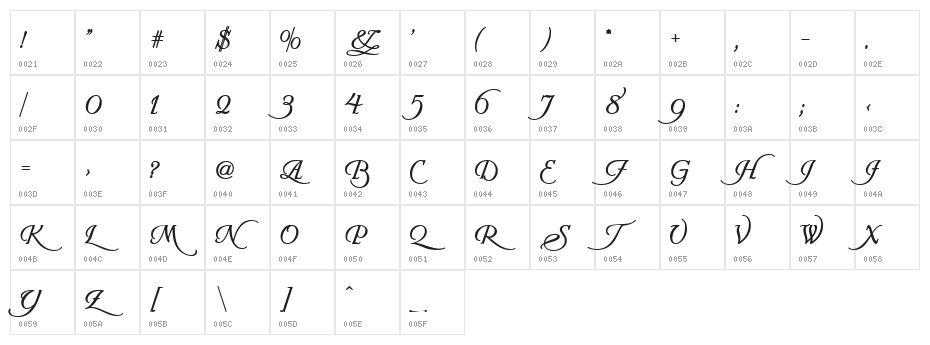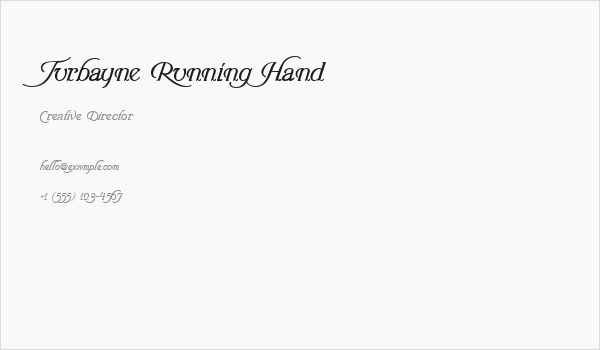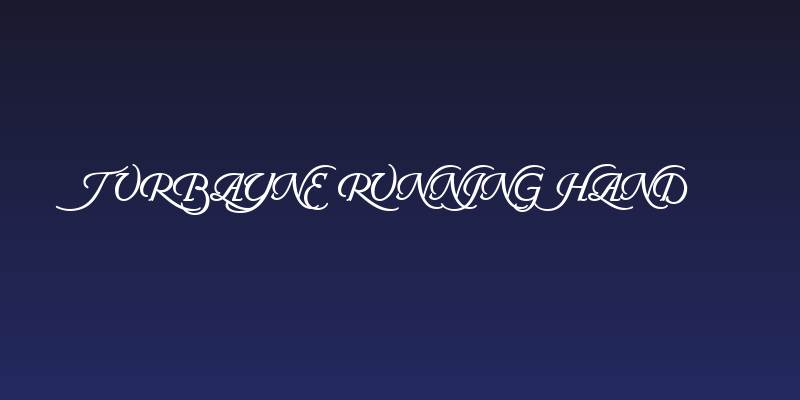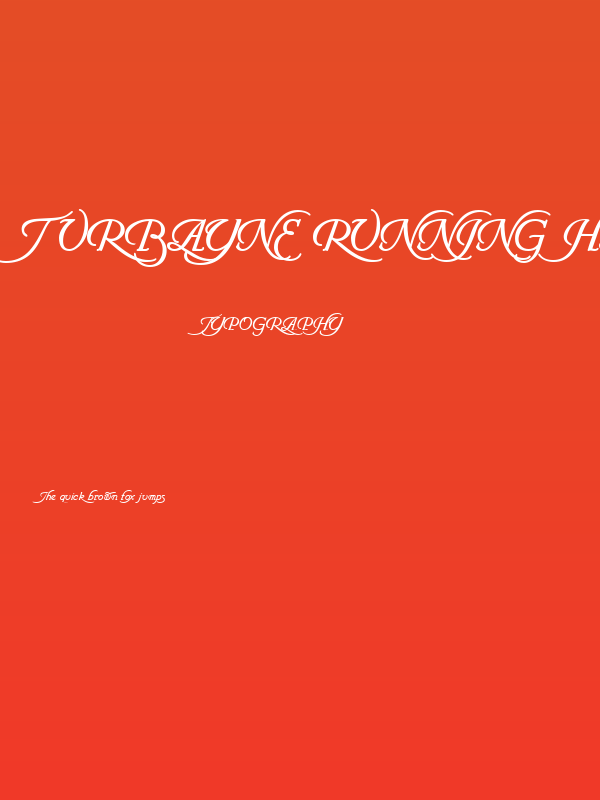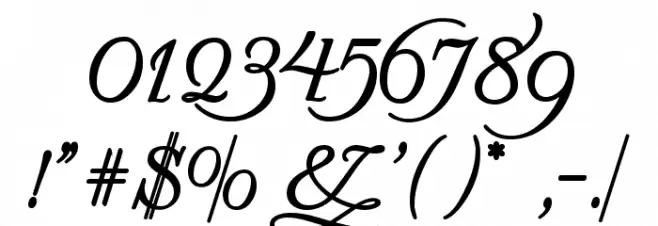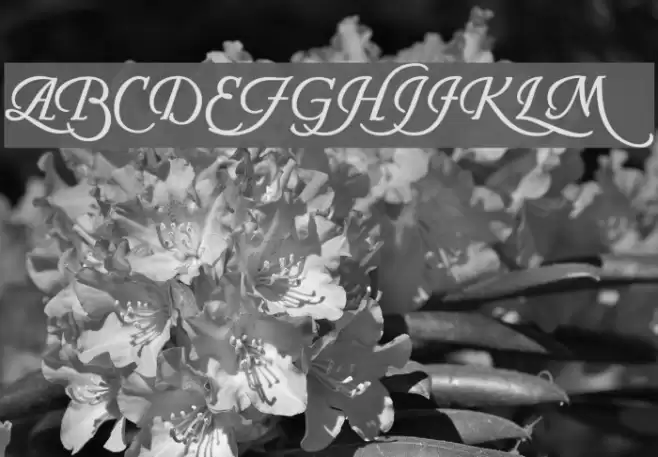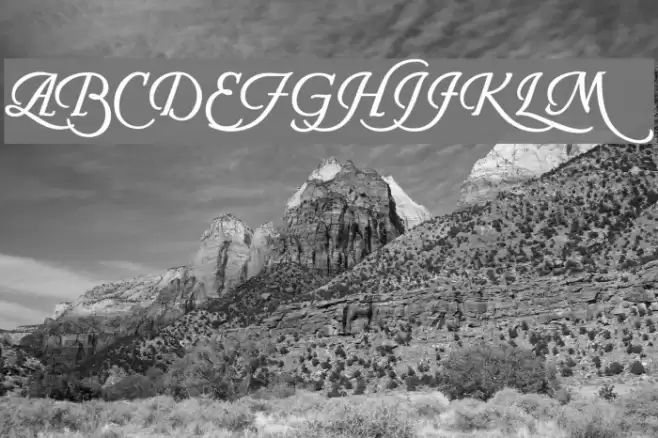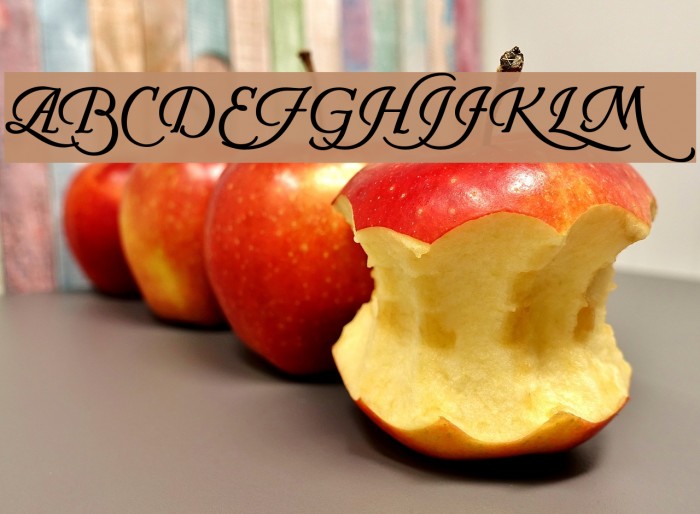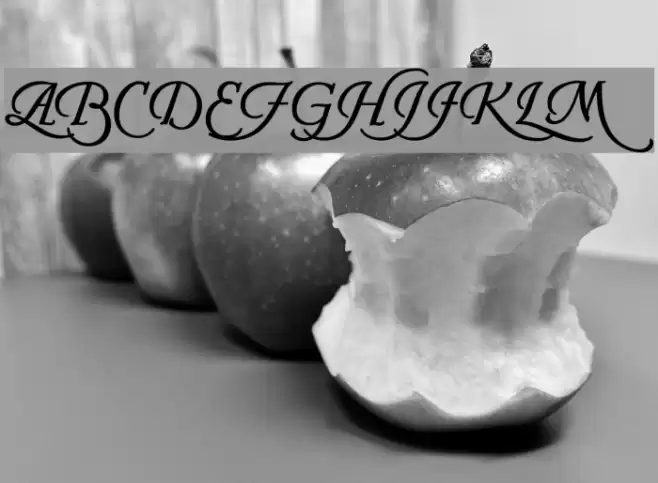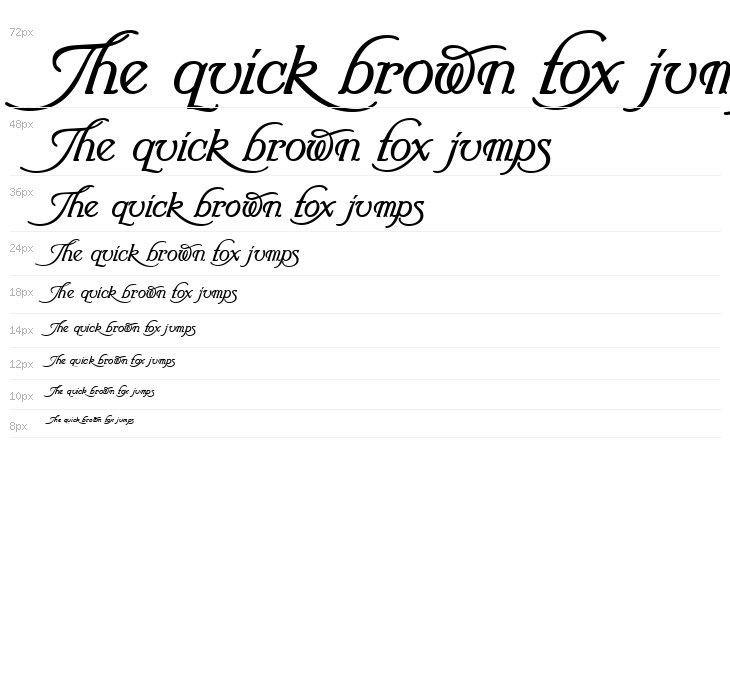
Turbayne Running Hand Font
✎ Script
| Gesamtstil | Elegant, Decorative |
| Anwendungsfall | Logos, Invitations, Decorative text |
| Vorgeschlagene Projekte | Wedding invitations, elegant branding, personal stationery, and artistic projects. |